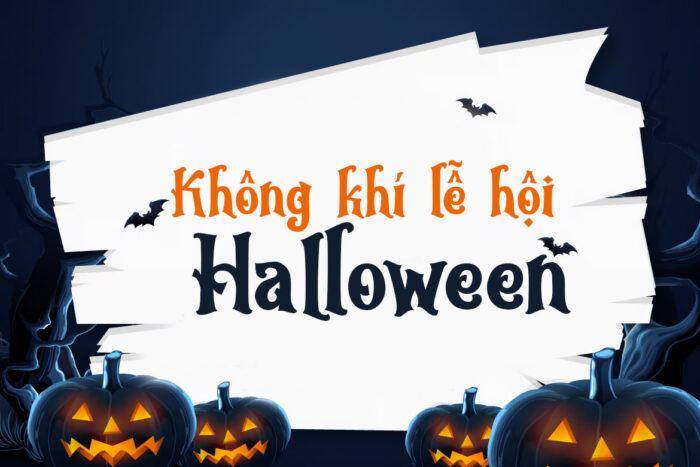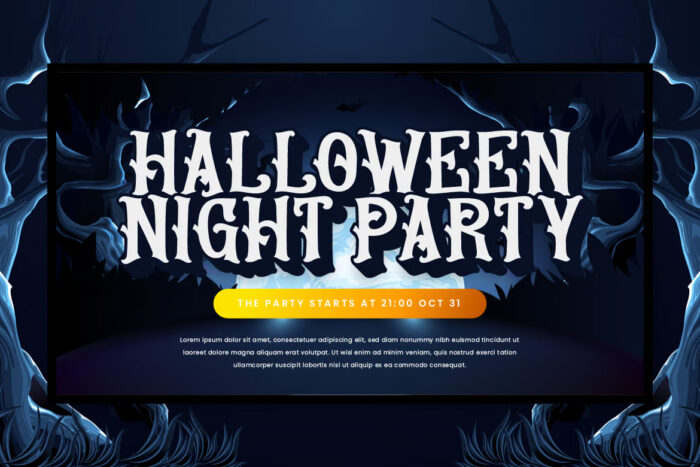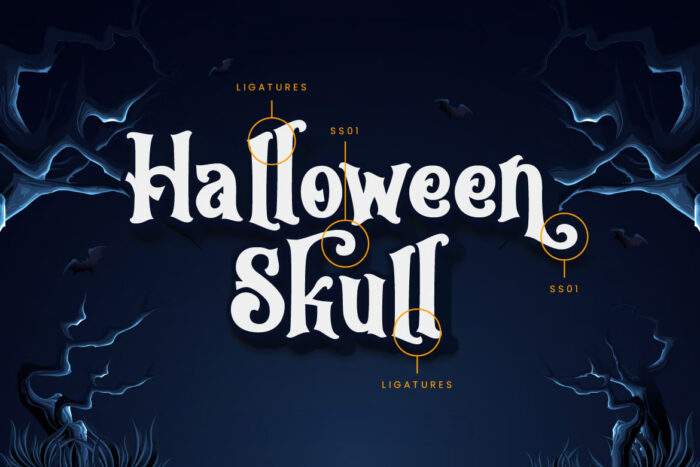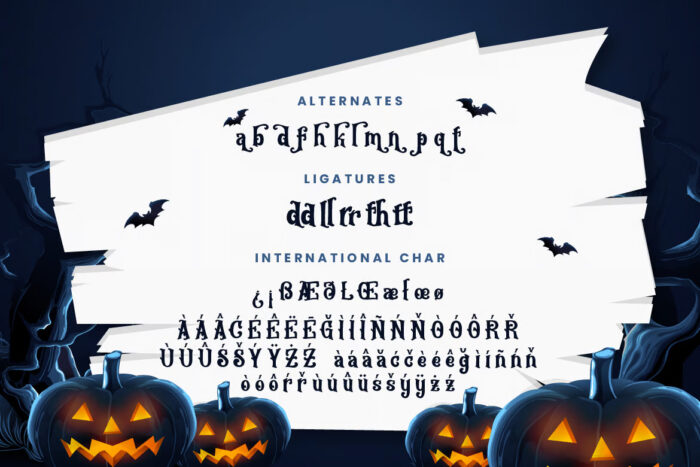
DVN Wicked Việt hóa – Font chữ uốn lượn cho ngày Halloween
DVN – Wicked là một font chữ đầy phong cách, lấy cảm hứng từ không khí ma mị của Halloween. Với những đường cong mạnh mẽ và chi tiết uốn lượn tinh tế, DVN – Wicked mang lại cảm giác rùng rợn nhưng đầy quyến rũ. Các ký tự được thiết kế độc đáo, tạo sự cân đối giữa sự cổ điển và hiện đại, phù hợp cho các dự án sáng tạo, áp phích lễ hội, hoặc thương hiệu mang chủ đề kỳ bí. Font này đặc biệt nổi bật khi sử dụng cho tiêu đề lớn, tạo điểm nhấn ấn tượng và cuốn hút. Màu sắc tối và các chi tiết gothic càng làm tăng thêm tính kịch tính và sự bí ẩn cho thiết kế. DVN – Wicked chắc chắn sẽ làm hài lòng những ai đang tìm kiếm một font chữ đậm chất “huyền bí” và “đáng sợ”, nhưng không kém phần cuốn hút và khác biệt.